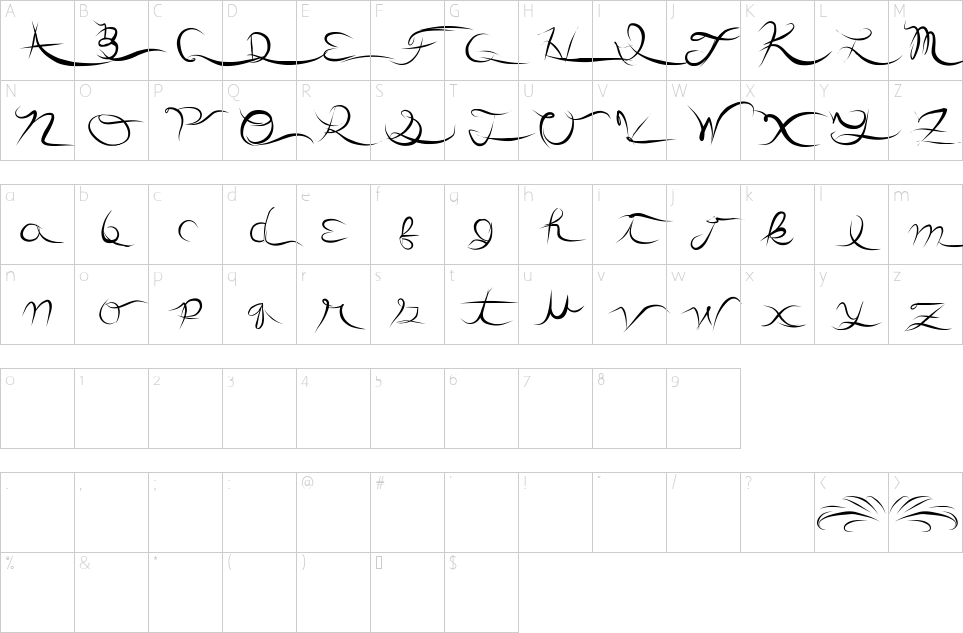
Another Party Font
A fonte ‘Another Party’ traz uma atmosfera vibrante e descontraída, perfeitamente adaptada para ambientes de festa ou ocasiões divertidas. Ela foi projetada pela Xerographer Fonts e já foi baixada 4.493 vezes. A sua tipografia informal e colorida combina perfeitamente com eventos sociais e ocasiões memoráveis, tornando-a uma escolha ótima para designers que procuram um estilo alegre e moderno. Instale ‘Another Party’ e encha seus designs de vida e diversão.
Mapa de caracteres da fonte Another Party Font